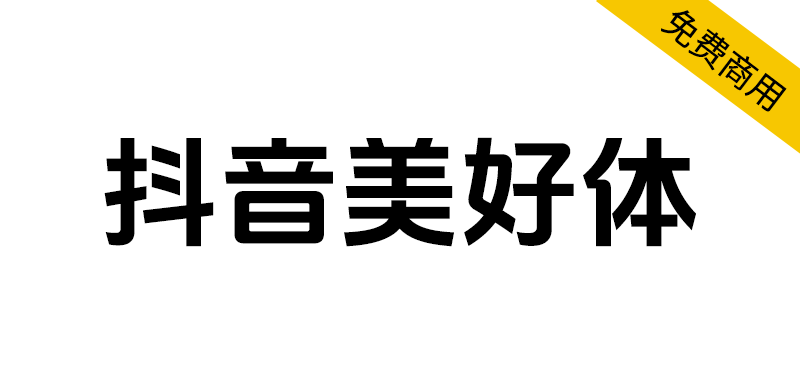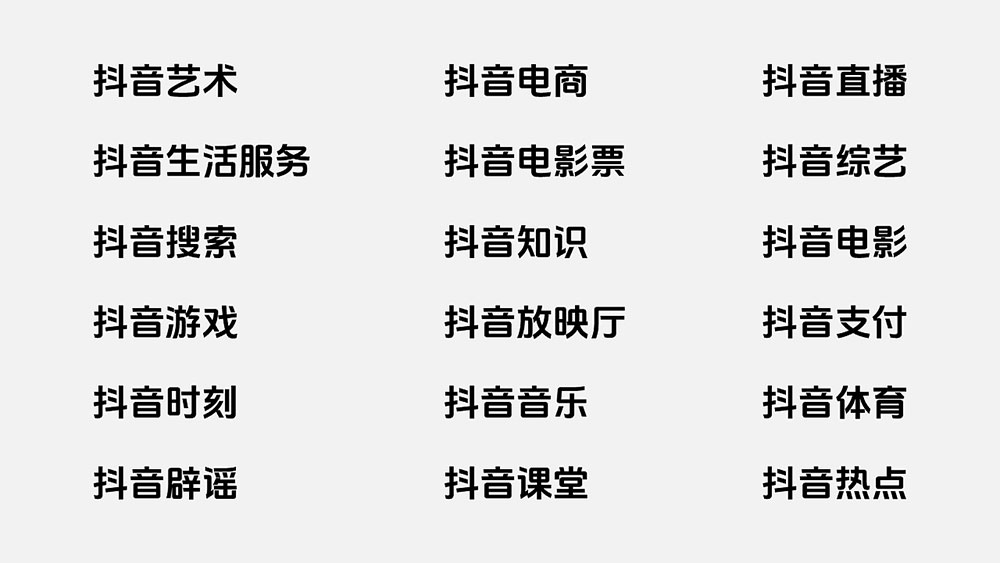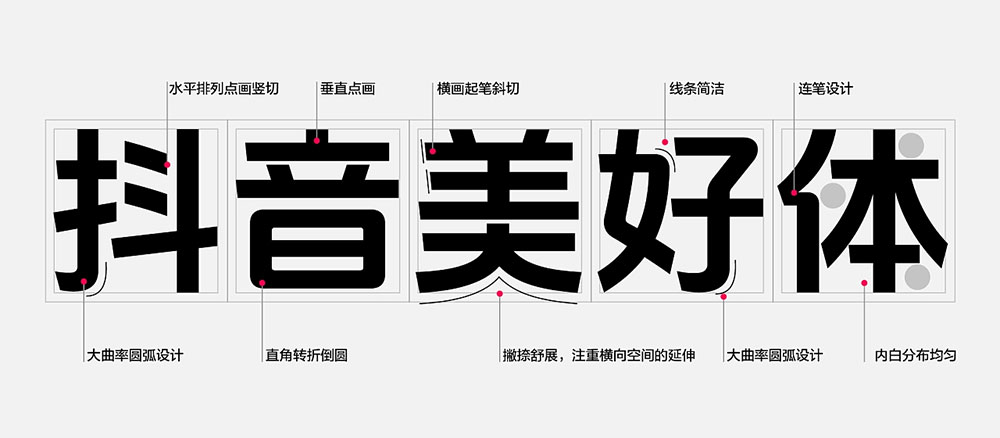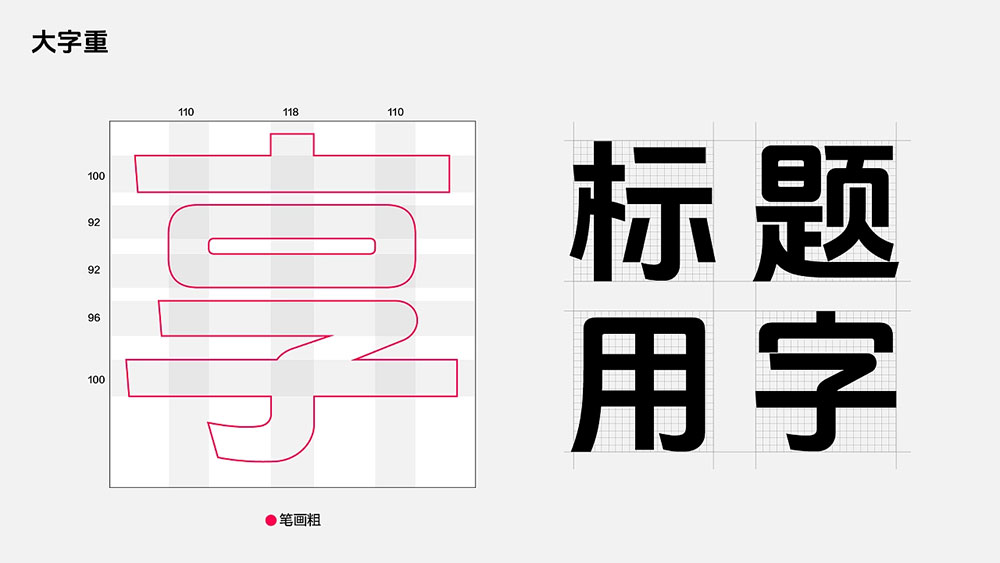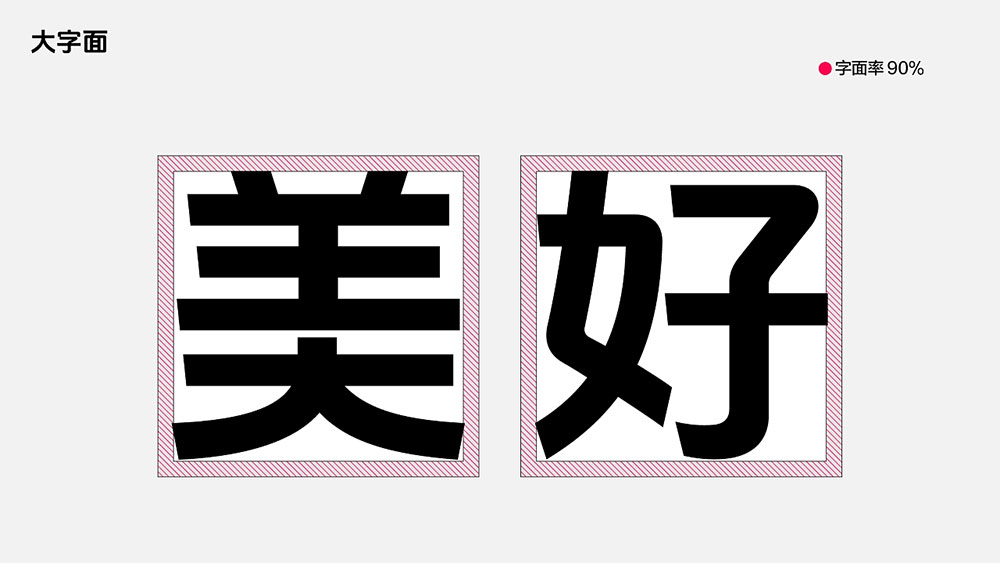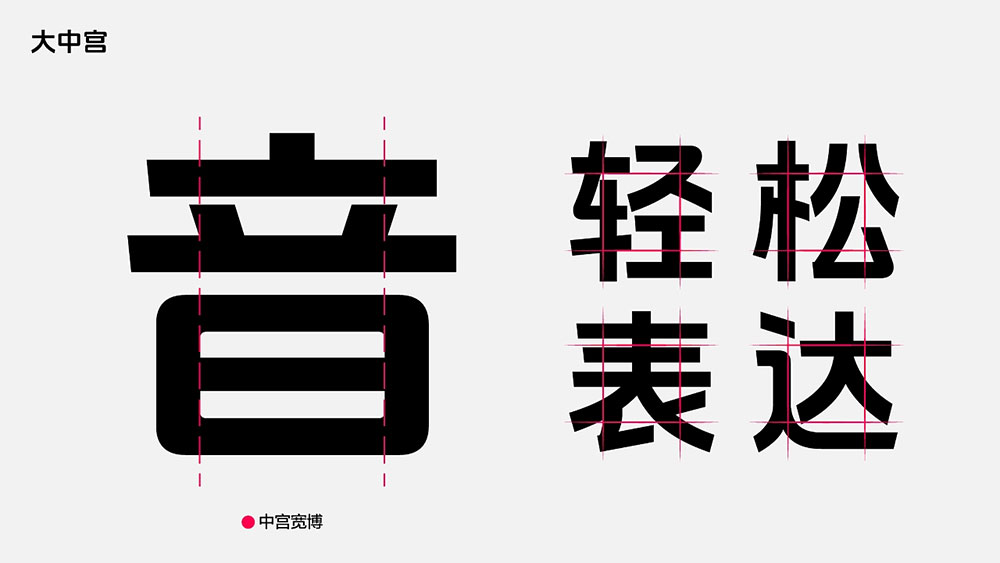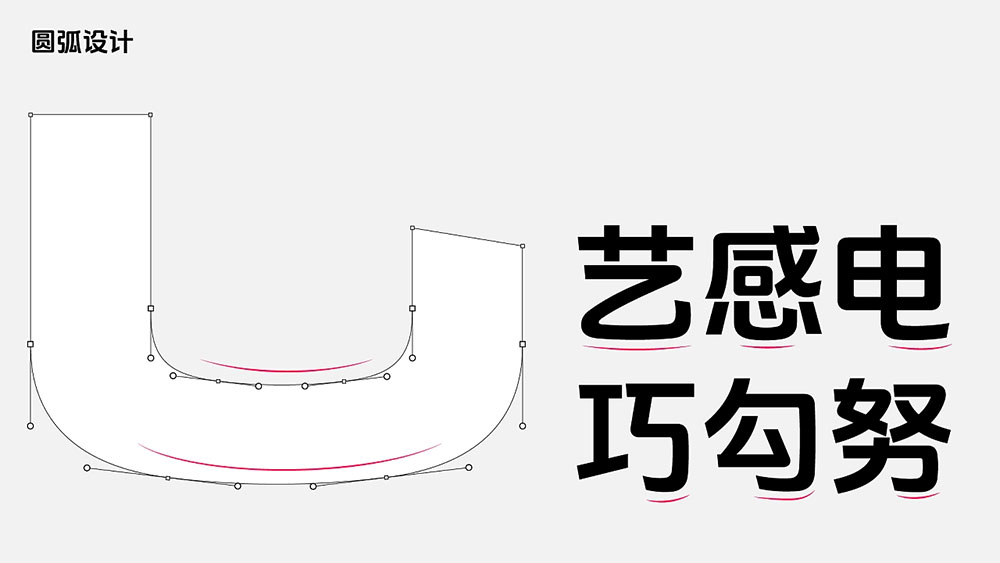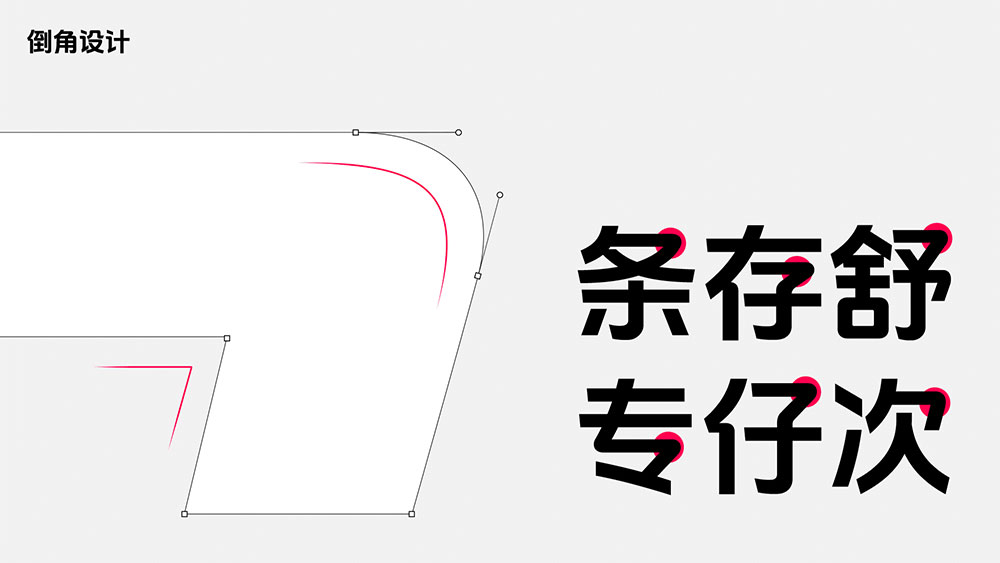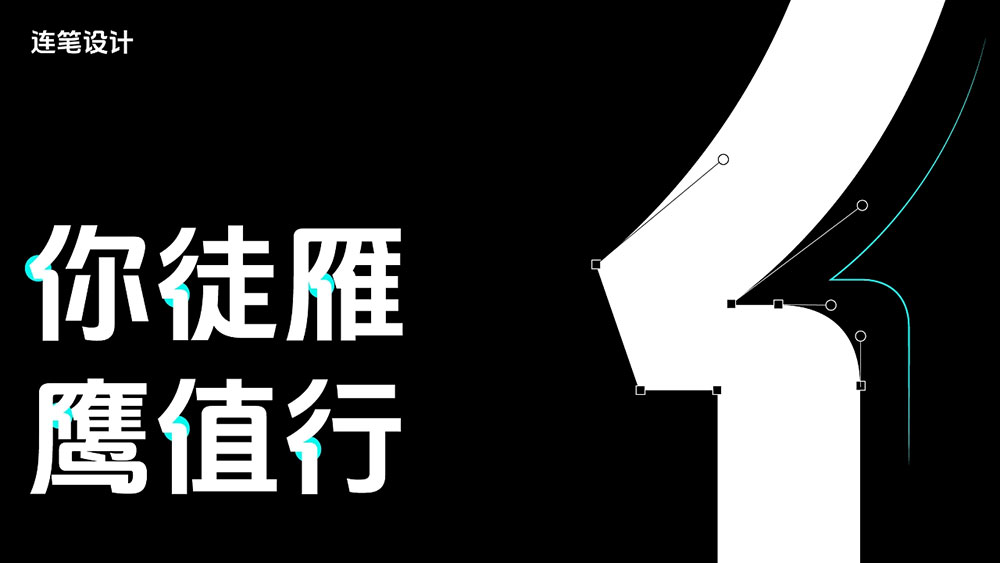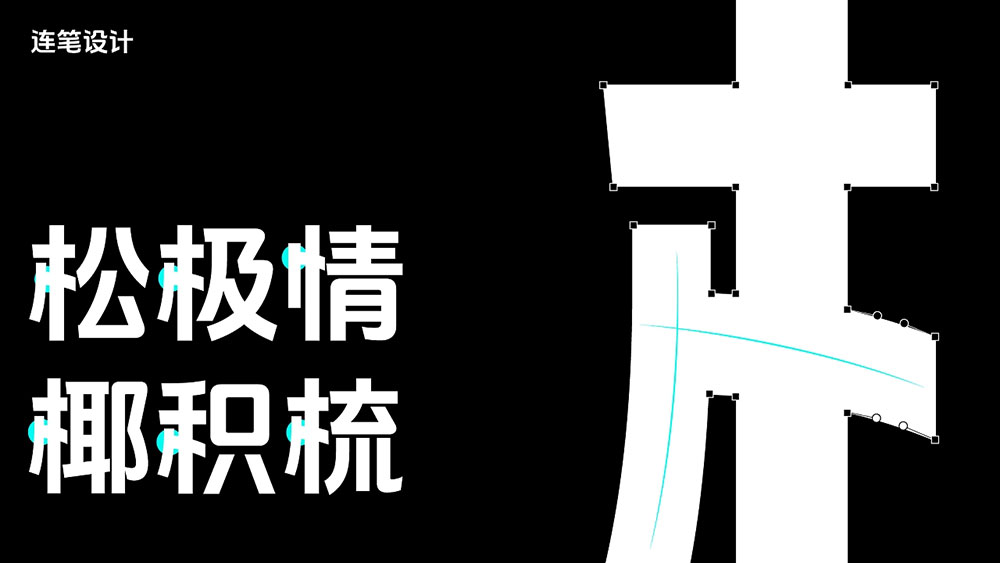
2023年,抖音已经从短视频平台发展为多体裁内容创作与分享平台,将优质内容带给用户的同时,更鼓励每一个人轻松创作与分享,去发现美好、传递美好。为了更好地传播“记录美好生活”的品牌理念,更好地满足品牌长远发展,打造优质的内容创作与产品体验,抖音体验设计中心与方正字库联合设计开发了一款简洁大方、清晰易读,同时兼具现代气质与人文属性的品牌定制字体——抖音美好体。
抖音美好体包含6763个中文字符,682个西文及数字符号,执行国家GB2312-80简体中文编码字符标准。作为品牌标准字体,抖音美好体将会率先用于抖音及其子品牌中,助力品牌视觉形象的统一,提升品牌的官方性、权威感。
场景赋能,助力业务发展:为了更好地以品牌赋能产品与业务,满足抖音端内不同场景的字体应用诉求,抖音体验设计中心团队将西文及数字字符拓展至5种不同粗细、宽窄,提升了字体与产品场景的适配度。除了全量上线抖音端内核心场景以外,抖音美好体已被广泛用于抖音市场传播场景,同时已内嵌于剪映、醒图等产品,抖音美好体将不断地助力业务发展。
方寸之间,塑造品牌差异:差异化的品牌视觉形象,有助于塑造差异化的品牌调性。抖音美好体通过字体骨架搭建、笔画细节设计等细节,塑造出“沉稳内敛、自然舒适”的字体性格,与抖音带给人们“轻松、自然、舒适”的产品体验遥相呼应,传递出抖音独特的品牌调性与感受。
抖音美好体提取了“抖音”logo字体简约清新的风格特征,为适应标题场景的使用,被打造为笔画较粗的大字重字体;90%的大字面率,呈现出美观大方、清晰易读的视觉风格;大中宫设计,使得字体更加舒展饱满,字体具有极强的识别特征。
为构建品牌字体的独特性,抖音美好体的笔画细节采用了非常规的圆弧设计和倒角设计。弯勾笔画采用大曲率圆弧曲线,均匀顺滑的线条设计使得字体更流畅优美,更具视觉韧性。折笔笔画则在平衡字体易读性和识别度的基础上,采用了内直外弧的倒角方式,传递出一种“刚柔并济”的人文气息。
书法融合,传承传统文化:书法是中国传统文化的重要组成部分,笔画、结构、布局等元素都蕴含着丰富的文化内涵和审美价值。抖音美好体将传统书法文化中的书写感、流畅感与现代字体设计相结合,借鉴了行书中连笔书写一气呵成的精髓,形成独特的连笔设计,将“灵动流畅、收放自如”的视觉体验与抖音“轻松、自然、舒适”的产品体验融为一体。
抖音美好体同样借鉴书法中笔锋的概念,将发笔时顺势落笔、笔锋显露在外的“露锋”笔法,转换为横笔斜切的设计手法,在保留书写感的同时,增加字体的视觉变化节奏。
中西匹配,统一视觉气质:为了满足抖音全生态全场景的标题使用需求,抖音美好体搭配了具有几何风格的西文字符,字形简洁干练、现代时尚,同时在细节上延续了中文的圆弧及横笔画斜切的特征,中西文匹配使用时呈现出一致的视觉气质。